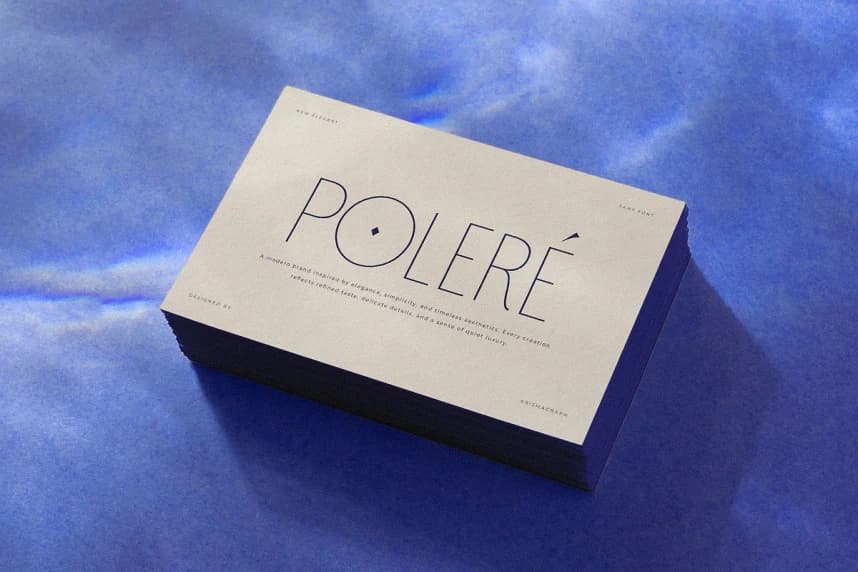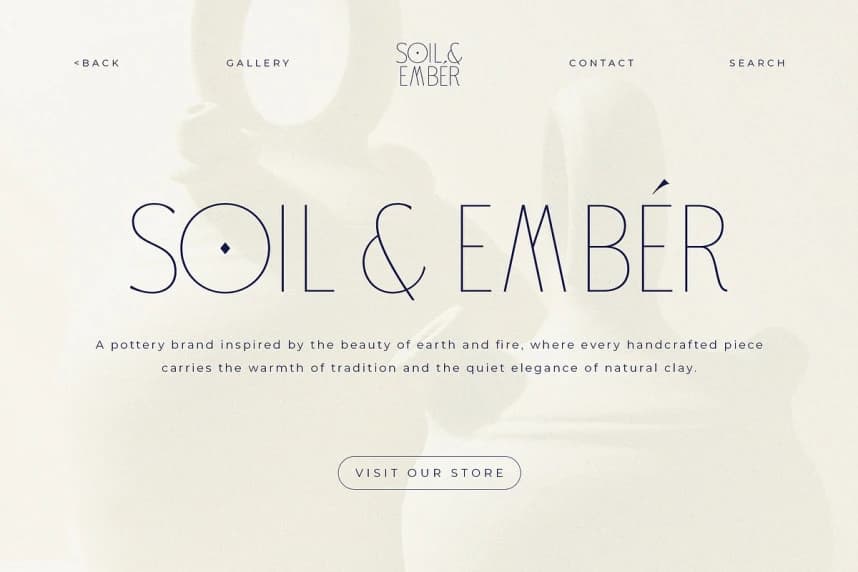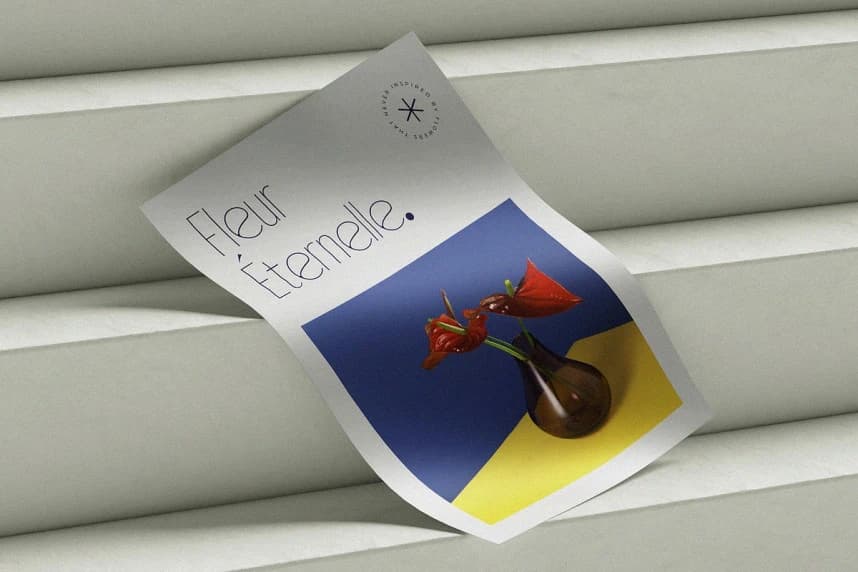
Qunotz Yazı Tipi
Qunotz Font, hassas işçilikle üretilmiş ultra ince geometrik bir gösterge sans serif fontudur ve negatif alanı bir tasarım ifadesine dönüştürür. Saf dairesel geometri üzerine kurulu olan bu fontun kılcal hatları ve geniş açık hacimleri belirgin bir görsel imza yaratır — havadar, mimari ve belirgin b
Qunotz Font, hassas biçimde üretilmiş ultra ince geometrik bir display sans'tır ve negatif alanı bir tasarım ifadesine dönüştürür. Saf dairesel geometri üzerine kurulu olan ince hatları ve geniş açık iç alanları, ayırt edici görsel imza oluşturuyor — eterik, mimari ve belirgin biçimde çağdaş.